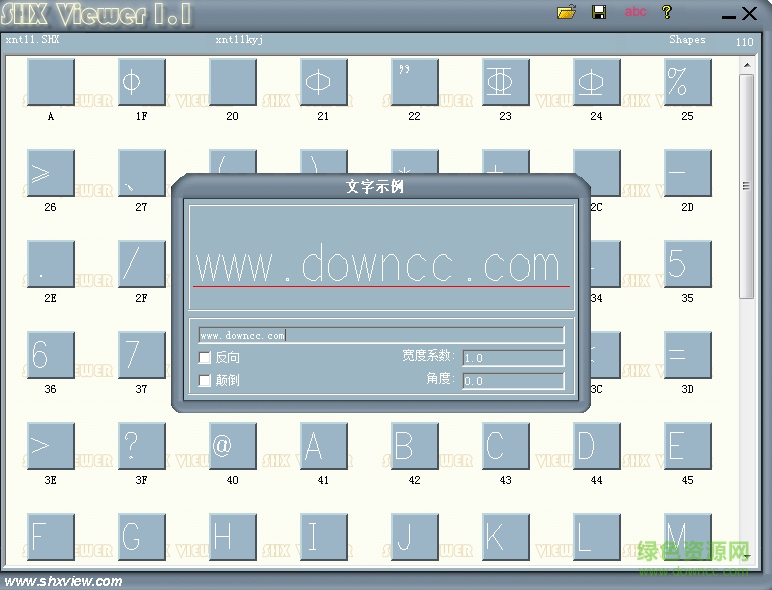
xnt11.shx字體是一款autocad的專(zhuān)用字體,shx字體雖然沒(méi)有一般的windows字體華麗漂亮,但該類(lèi)字體縮放方便,電腦顯示效果精細(xì),設(shè)計(jì)更便捷,有需要者快來(lái)綠色資源網(wǎng)下載吧!
cad里所稱的shx字體和大字體(也叫bigfont),都是autocad專(zhuān)用專(zhuān)有的字體。大字體也是shx字體,是shx字體的一種特殊形式。
特殊性:集成鋼筋1-4級(jí)鋼筋符號(hào);2次方上標(biāo)符號(hào);羅馬字2、3符號(hào);主要占用左鍵盤(pán)換房鍵位字符。